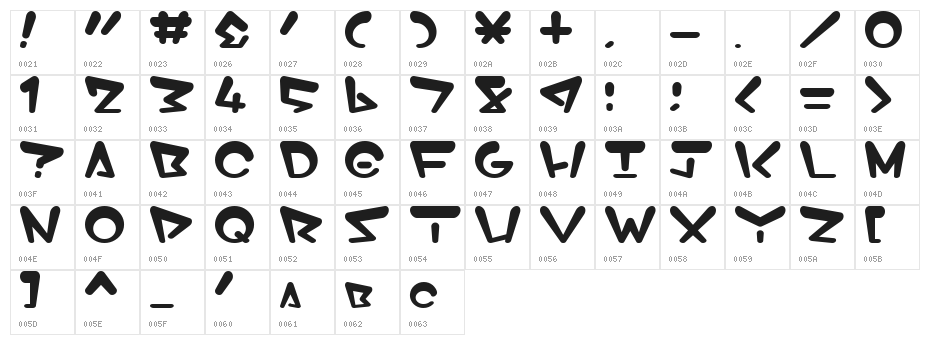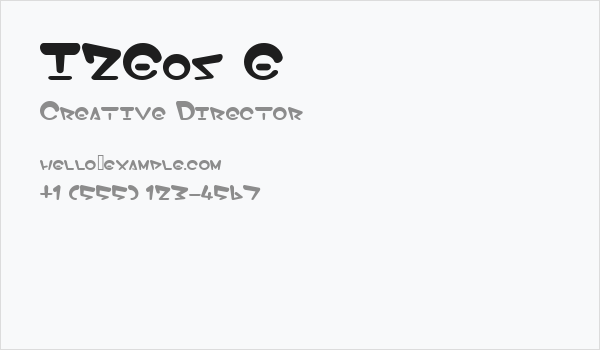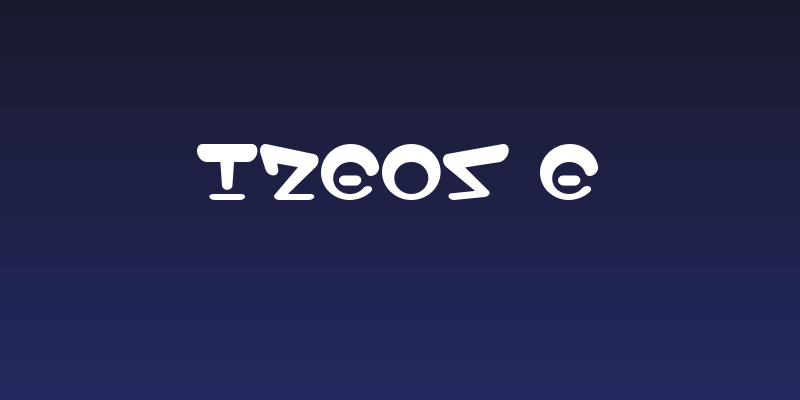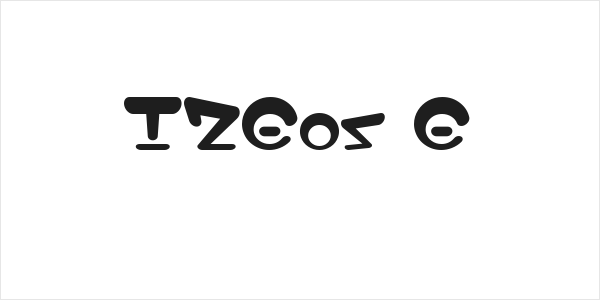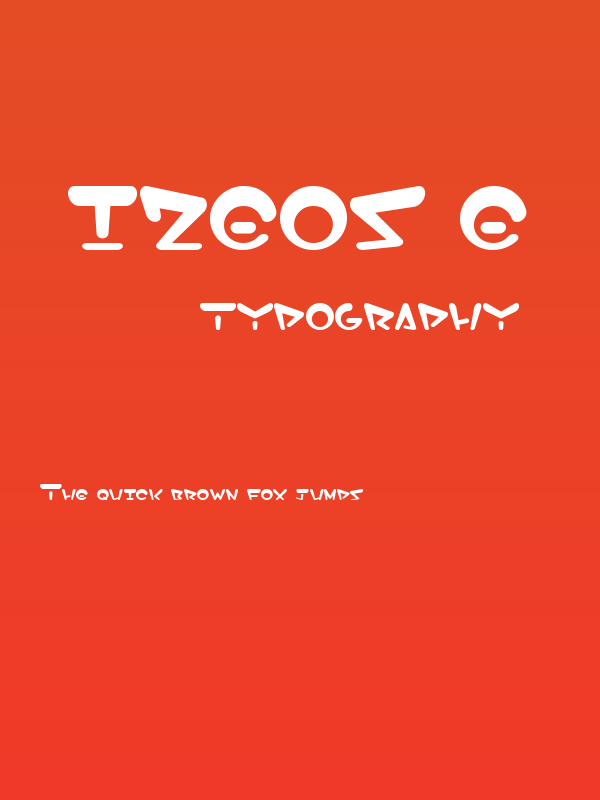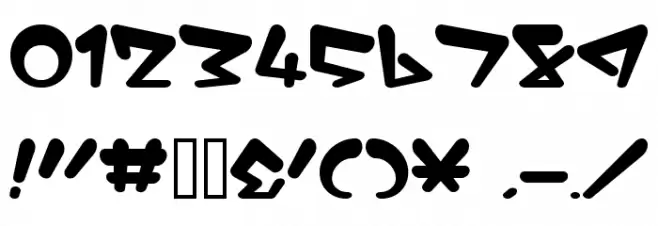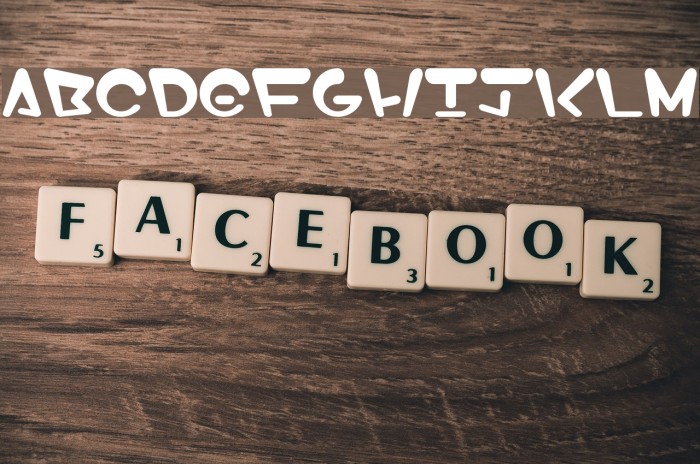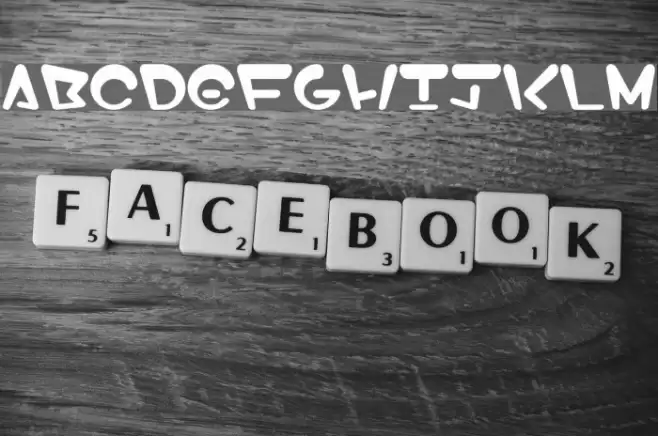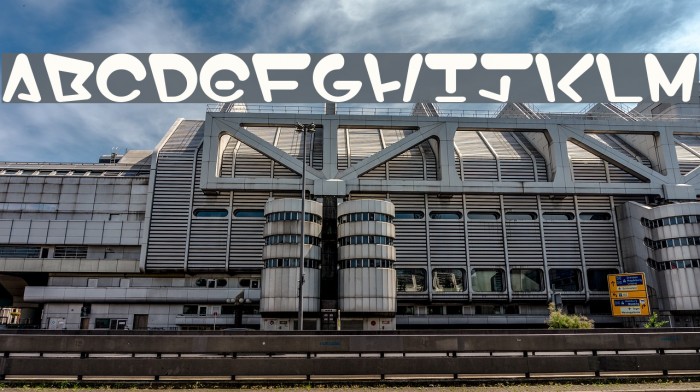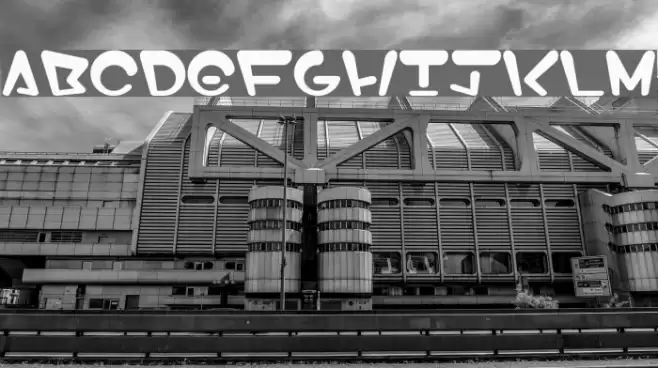
I2Eos E Font
| Style général | Modern, Decorative |
| Projets proposés | Ideal for sci-fi themed designs, video game graphics, posters, and branding that requires a modern and unique look. |